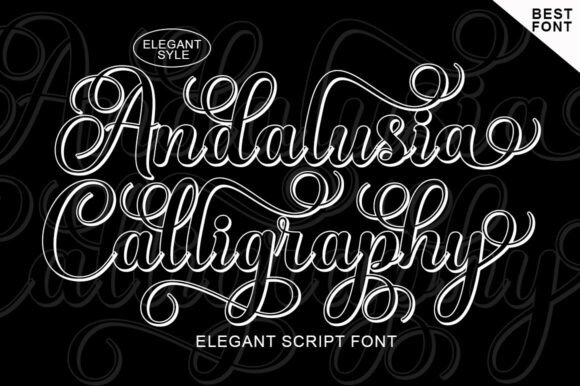
Andalusia Calligraphy
Ulasan Andalusia Calligraphy – Font Hand‑Written yang Elegan dan Unik
Jika Anda sedang mencari font tulisan tangan yang memberi kesan lembut namun tetap menonjol, Andalusia Calligraphy adalah pilihan yang tepat. Dirancang khusus untuk memberikan sentuhan artistik pada setiap proyek, font ini cocok untuk berbagai keperluan mulai dari undangan pernikahan hingga label produk makanan.
Keunggulan Utama Andalusia Calligraphy
- Desain Halus dan Elegan – Garis‑garis tipis serta lengkungan yang natural membuat teks terlihat seolah‑olah ditulis dengan pena kaligrafi tradisional.
- Serbaguna – Ideal untuk letters, invitations, food packaging, titles, dan banyak lagi. Cocok dipadukan dengan desain modern maupun klasik.
- Mudah Dibaca – Meskipun memiliki gaya dekoratif, setiap huruf tetap jelas dan tidak mengorbankan keterbacaan.
Aplikasi Populer Andalusia Calligraphy
- Undangan pernikahan dan acara khusus
- Kartu ucapan dan letterhead perusahaan
- Label kemasan makanan dan minuman premium
- Judul buku, poster, dan materi promosi
- Desain logo dengan sentuhan personal
Mengapa Memilih Andalusia Calligraphy?
Di era desain yang penuh persaingan, detail kecil dapat menjadi pembeda utama. Andalusia Calligraphy menawarkan karakter visual yang unik tanpa harus mengorbankan kejelasan pesan. Dengan kombinasi estetika klasik dan fleksibilitas modern, font ini membantu brand Anda menonjol di pasar.
Kesimpulan
Andalusia Calligraphy bukan sekadar font tulisan tangan, melainkan alat kreatif yang menambah nilai estetika pada setiap desain. Dengan kehalusan, kepraktisan, dan lisensi komersial yang fleksibel, font ini layak menjadi pilihan utama bagi desainer, pemilik bisnis, dan siapa saja yang menginginkan tampilan visual yang memukau.